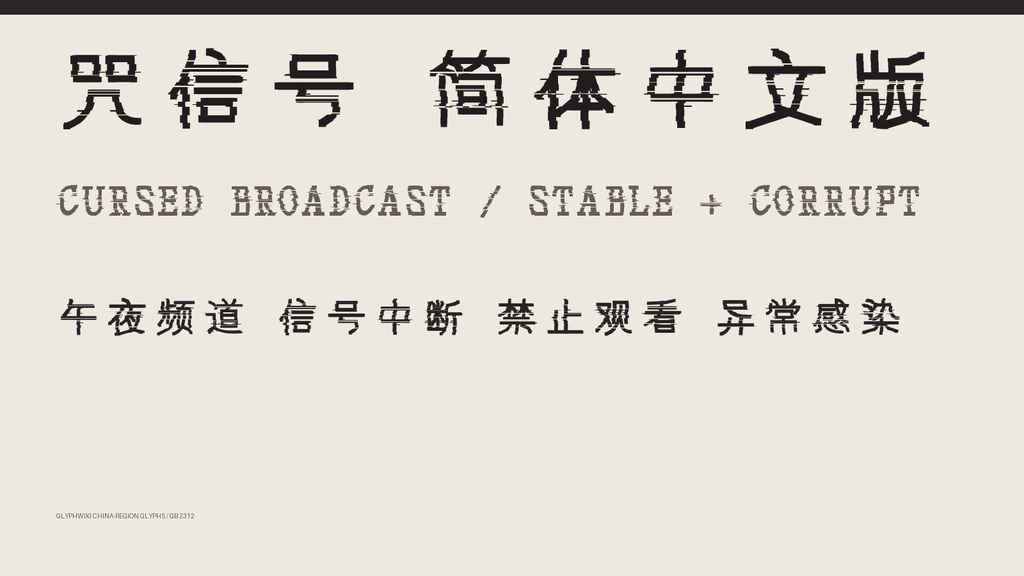
咒信号 SC|简体字6,763字・2款字体
【咒信号 SC / JUSHINGO SC】 文字被水平同步错位切开,在残影、噪点与信号缺损之间勉强重组。 这是一套以受诅咒的模拟电视和异常通信为主题的简体中文恐怖字体。 Stable 保留较稳定的识读轮廓,Corrupt 则让画面产生更强烈的崩坏与干扰。 ■ 价格 1,480日元 ■ 内含字体 ・Stable:清晰度较高的信号错位版 ・Corrupt:噪声与缺损更强的故障版 ■ 格式 TrueType(TTF)2款 / Windows・macOS ■ 收录 每款共7,542个字码(包含空格) GB 2312 全部汉字:6,763字 拉丁字母、数字、半角与全角符号:779个 ■ 特点 ・横向扫描线、同步错位与信号断裂 ・残影和模拟电视噪声般的轮廓 ・汉字、英文字母、数字和符号使用统一的故障表现 ・Stable / Corrupt 两种干扰强度 ■ 推荐用途 恐怖游戏、VHS影像、监控画面、异常广播、科幻界面、音乐封面、视频标题、直播画面、海报与标志 ■ 使用许可 可用于个人及商业项目。可用于标志、视频、游戏、印刷品、直播素材、同人及商业作品。 无需署名。禁止重新分发、共享或转售字体文件。 详细条款请查看ZIP内的使用许可。 ※含有横向断裂和细小噪声,推荐用于28px以上的标题。